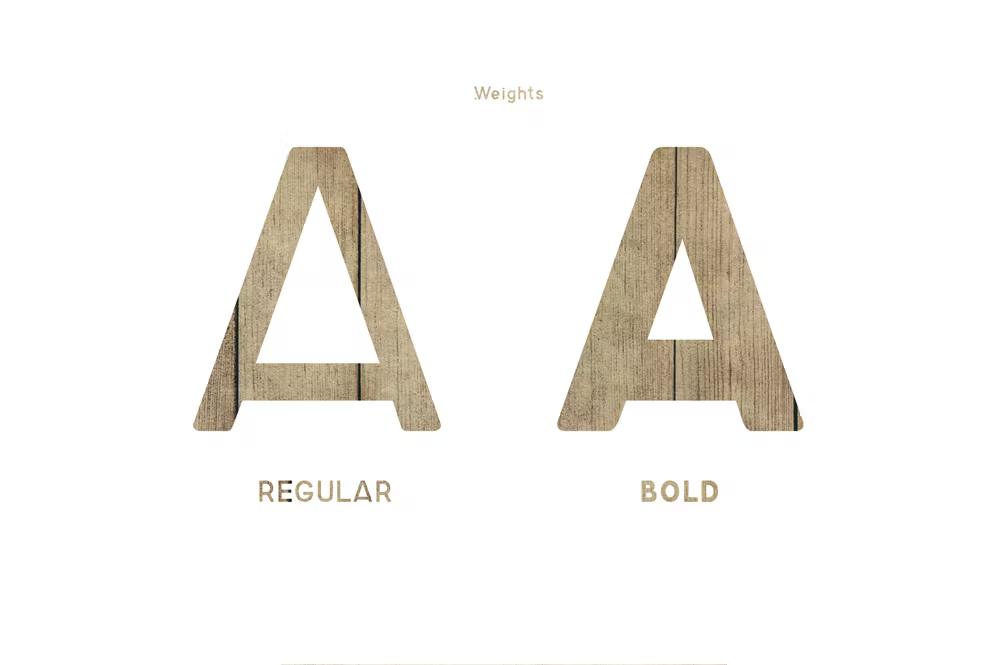
Superstar Grotesk Font
Superstar Grotesk est une interprétation libre des premières versions cyrilliques de Royal Grotesk et Akzidenz Grotesk, plus tard la police « Roublennaya » est le même artiste pop inamovible qui s’est attardé au sommet des charts typographiques jusqu’à l’ère numérique, et a formé l’image du L’alphabet cyrillique au XXe siècle.